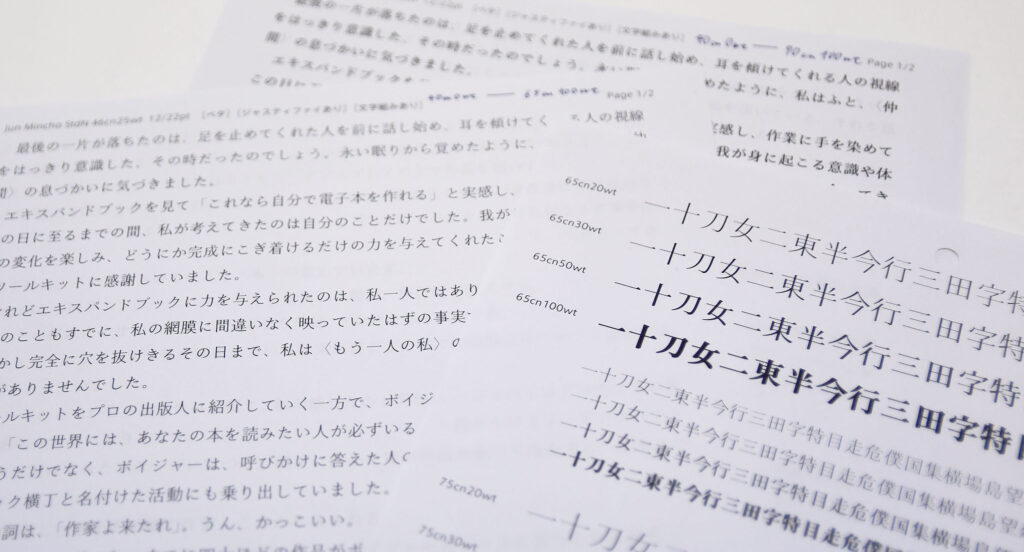
純明朝 開発ストーリー 3「コントラストの検討:純明朝 ヘッドライン・純明朝 ヘアライン」
純明朝シリーズではコントラストが異なる標準・ヘッドライン・ヘアラインがあります。 エレメントの先端や、漢字の横画の太さの比率で印象が大きく変わるため、何度もテストを行いました。
ヘアラインは極限まで細い数値に設定し、ヘッドラインではやや小さい文字のサイズでも横画が飛ばないギリギリの細さはどのくらいかなどを試しました。標準では各ウエイトでコントラストを変えて、テキストサイズでもすっきりと見えて安定感がある値にしました。少しの値で思っている印象よりも重くなってしまったり、その微妙な調整をするのが難しかったです。